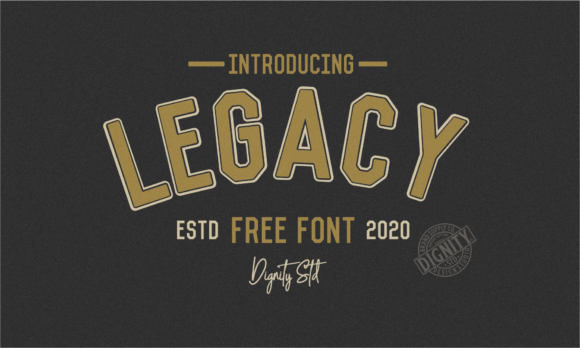
Creativefabrica Legacy Font
[Creativefabrica] Legacy Font
Legacy - это современный шрифт без засечек.
Используйте этот шрифт для любого проекта, требующего индивидуального подхода!